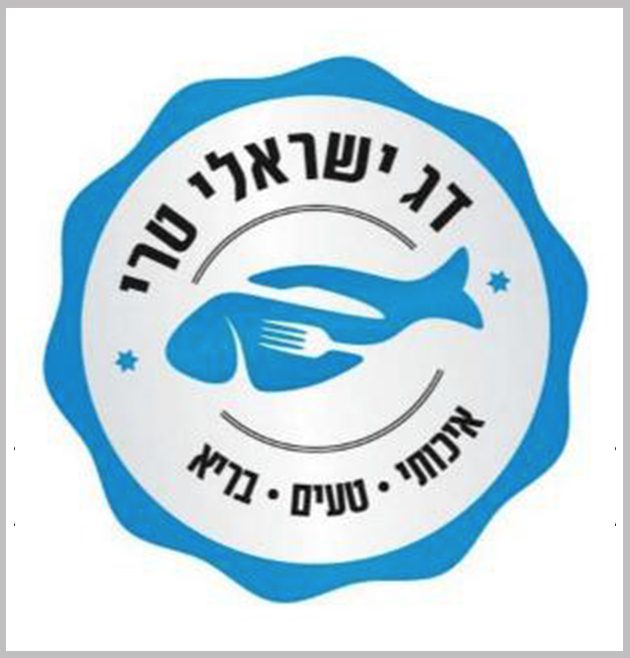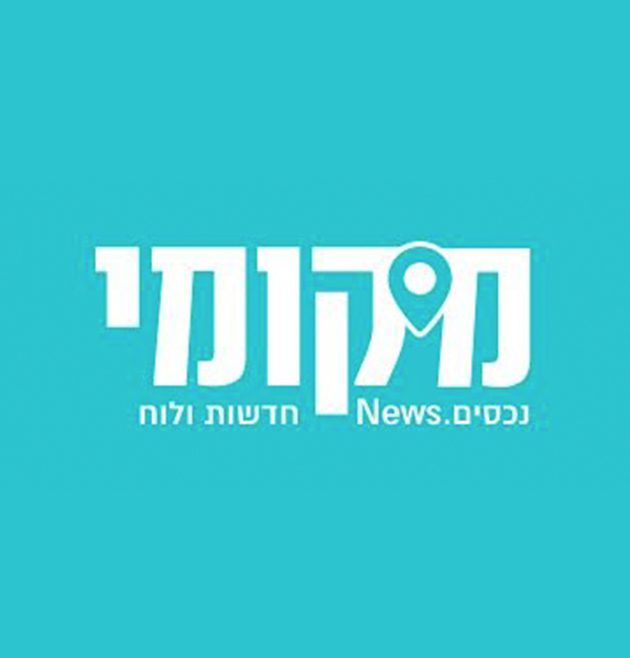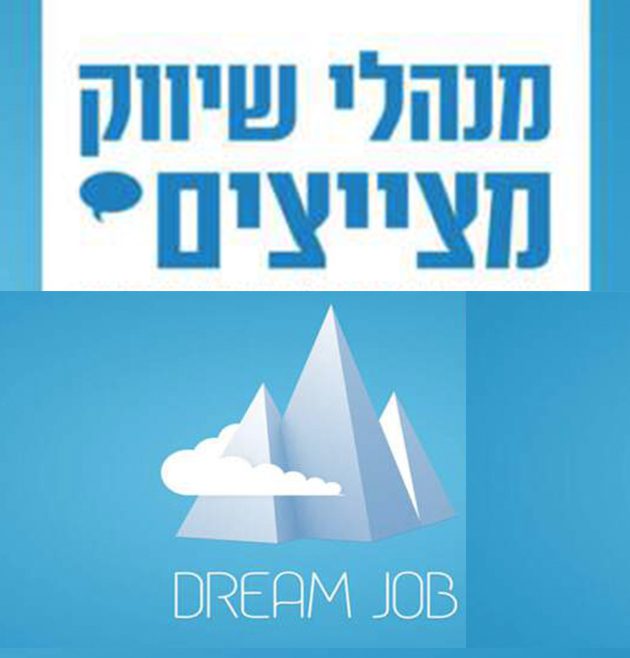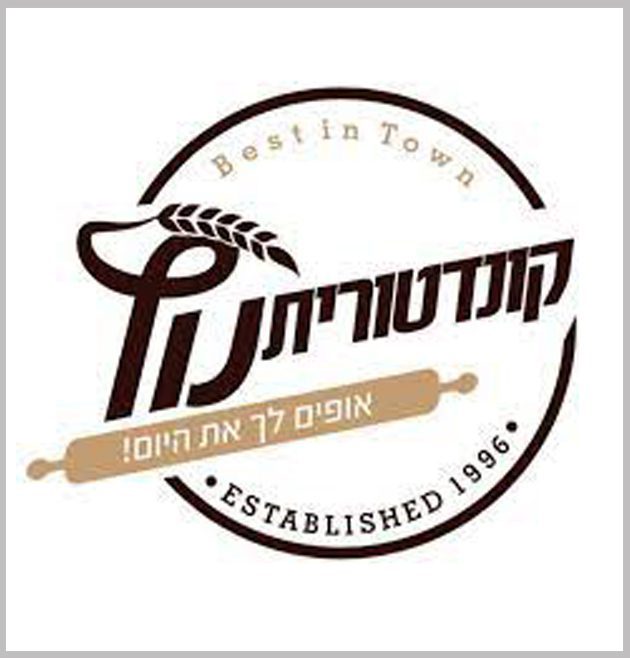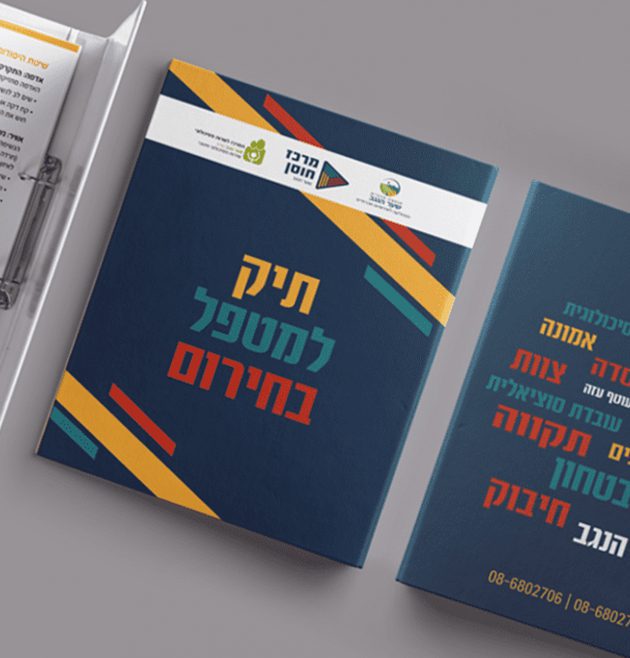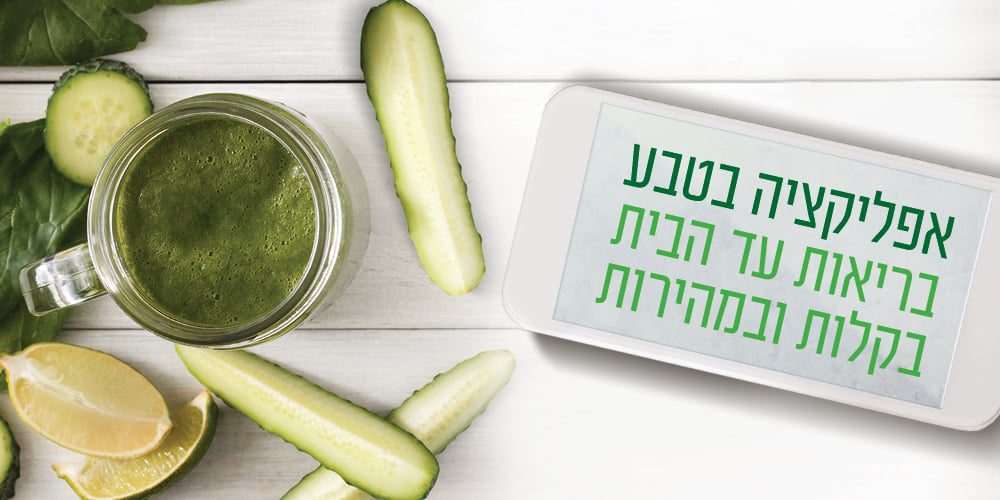
טיפוס אות מספר סידורי [3790] שימושי קלאסי ואלגנטי
מתבטא באופן בו התכונות לובשות צורה
אטמוספירה של אות
מקצב סופי חזק
האלפבית העברי מאכלס בתוכו מטען תרבותי רב-ערך. מטען זה מתבטא באופן בו התכונות לובשות צורה כאותיות המתקיימות יחד בהרמוניה. אות היא אמנם היחידה הקטנה והבסיסית ביותר במערך הטיפוגרפי השלם, אבל למרות מימדיה לאות יש השפעה משמעותית על המבנה החזותי של המילה, המשפט ולבסוף על תצורת הטקסט המעומד בשלמותו. פיתוח טיפוס אות, הינו תהליך של התגבשות הצורות וחיפוש אחר איזון בין התכונה של המבנה הכללי לבין התכונה הייחודית של כל אחת מהאותיות. אות היא אמנם היחידה הקטנה והבסיסית ביותר שבכל המערך הטיפוגרפי אבל למרות מימדיה לאות יש השפעה משמעותית על כל המבנה החזותי של המילה, המשפט ולבסוף גם על תצורת הטקסט המעומד בשלמותו. תפיסת העיצוב בפונטביט היא חופש וחדוות יצירה עם הערכה רבה למקור האלפבית העברי שמאכלס בתוכו מטען תרבותי רב-ערך. מטען זה מתבטא באופן בו התכונות לובשות צורה כאותיות המתקיימות יחד בהרמוניה. אות היא אמנם היחידה הקטנה והבסיסית ביותר במערך הטיפוגרפי השלם, אבל למרות מימדיה לאות יש השפעה משמעותית על המבנה החזותי של המילה, המשפט ולבסוף על תצורת הטקסט המעומד בשלמותו. פיתוח טיפוס אות, הינו תהליך של התגבשות הצורות וחיפוש אחר איזון בין התכונה של המבנה הכללי לבין התכונה הייחודית של כל אחת מהאותיות תפיסת העיצוב בפונטביט היא חופש וחדוות יצירה עם הערכה רבה למקור האלפבית העברי שמאכלס בתוכו מטען תרבותי רב-ערך. מטען זה מתבטא באופן בו התכונות לובשות צורה כאותיות המתקיימות יחד בהרמוניה. אות היא אמנם היחידה הקטנה והבסיסית ביותר במערך הטיפוגרפי השלם, אבל למרות מימדיה לאות יש השפעה משמעותית על המבנה החזותי של המילה, המשפט ולבסוף על תצורת הטקסט המעומד בשלמותו. פיתוח טיפוס אות, הינו תהליך של התגבשות הצורות וחיפוש אחר איזון בין התכונה של המבנה הכללי לבין התכונה הייחודית של כל אחת מהאותיות.
תפיסת העיצוב בפונטביט היא חופש וחדוות יצירה עם הערכה רבה למקור האלפבית העברי שמאכלס בתוכו מטען תרבותי רב-ערך. מטען זה מתבטא באופן בו התכונות לובשות צורה כאותיות המתקיימות יחד בהרמוניה. אות היא אמנם היחידה הקטנה והבסיסית ביותר במערך הטיפוגרפי השלם, אבל למרות מימדיה לאות יש השפעה משמעותית על המבנה החזותי של המילה, המשפט ולבסוף על תצורת הטקסט המעומד בשלמותו. פיתוח טיפוס אות, הינו תהליך של התגבשות הצורות וחיפוש אחר איזון בין התכונה של המבנה הכללי לבין התכונה הייחודית של כל אחת מהאותיות. אות היא אמנם היחידה הקטנה והבסיסית ביותר שבכל המערך הטיפוגרפי אבל למרות מימדיה לאות יש השפעה משמעותית על כל המבנה החזותי של המילה, המשפט ולבסוף גם על תצורת הטקסט המעומד בשלמותו. תפיסת העיצוב בפונטביט היא חופש וחדוות יצירה עם הערכה רבה למקור האלפבית העברי שמאכלס בתוכו מטען תרבותי רב-ערך. מטען זה מתבטא באופן בו התכונות לובשות צורה כאותיות המתקיימות יחד בהרמוניה. אות היא אמנם היחידה הקטנה והבסיסית ביותר במערך הטיפוגרפי השלם, אבל למרות מימדיה לאות יש השפעה משמעותית על המבנה החזותי של המילה, המשפט ולבסוף על תצורת הטקסט המעומד בשלמותו. פיתוח טיפוס אות, הינו תהליך של התגבשות הצורות וחיפוש אחר איזון בין התכונה של המבנה הכללי לבין התכונה הייחודית של כל אחת מהאותיות תפיסת העיצוב בפונטביט היא חופש וחדוות יצירה עם הערכה רבה למקור האלפבית העברי שמאכלס בתוכו מטען תרבותי רב-ערך. מטען זה מתבטא באופן בו התכונות לובשות צורה כאותיות המתקיימות יחד בהרמוניה. אות היא אמנם היחידה הקטנה והבסיסית ביותר במערך הטיפוגרפי השלם, אבל למרות מימדיה לאות יש השפעה משמעותית על המבנה החזותי של המילה, המשפט ולבסוף על תצורת הטקסט המעומד בשלמותו. פיתוח טיפוס אות, הינו תהליך של התגבשות הצורות וחיפוש אחר איזון בין התכונה של המבנה הכללי לבין התכונה הייחודית של כל אחת מהאותיות.
אות היא אמנם היחידה הקטנה והבסיסית ביותר שבכל המערך הטיפוגרפי אבל למרות מימדיה לאות יש השפעה משמעותית על כל המבנה החזותי של המילה, המשפט ולבסוף גם על תצורת הטקסט המעומד בשלמותו. תפיסת העיצוב בפונטביט היא חופש וחדוות יצירה עם הערכה רבה למקור האלפבית העברי שמאכלס בתוכו מטען תרבותי רב-ערך. מטען זה מתבטא באופן בו התכונות לובשות צורה כאותיות המתקיימות יחד בהרמוניה. אות היא אמנם היחידה הקטנה והבסיסית ביותר במערך הטיפוגרפי השלם, אבל למרות מימדיה לאות יש השפעה משמעותית על המבנה החזותי של המילה, המשפט ולבסוף על תצורת הטקסט המעומד בשלמותו. פיתוח טיפוס אות, הינו תהליך של התגבשות הצורות וחיפוש אחר איזון בין התכונה של המבנה הכללי לבין התכונה הייחודית של כל אחת מהאותיות תפיסת העיצוב בפונטביט היא חופש וחדוות יצירה עם הערכה רבה למקור האלפבית העברי שמאכלס בתוכו מטען תרבותי רב-ערך. מטען זה מתבטא באופן בו התכונות לובשות צורה כאותיות המתקיימות יחד בהרמוניה. אות היא אמנם היחידה הקטנה והבסיסית ביותר במערך הטיפוגרפי השלם, אבל למרות מימדיה לאות יש השפעה משמעותית על המבנה החזותי של המילה, המשפט ולבסוף על תצורת הטקסט המעומד בשלמותו. פיתוח טיפוס אות, הינו תהליך של התגבשות הצורות וחיפוש אחר איזון בין התכונה של המבנה הכללי לבין התכונה הייחודית של כל אחת מהאותיות.